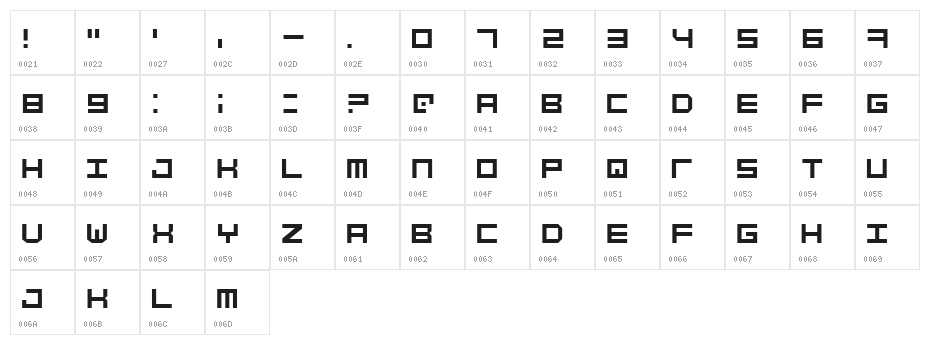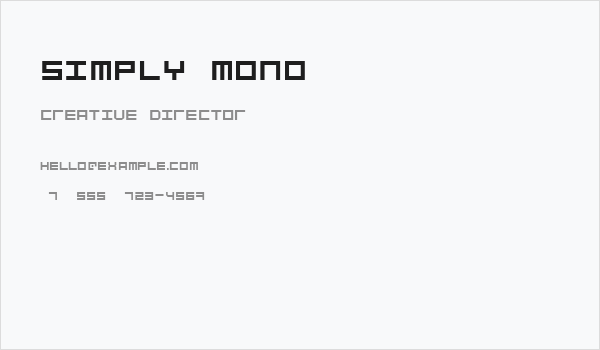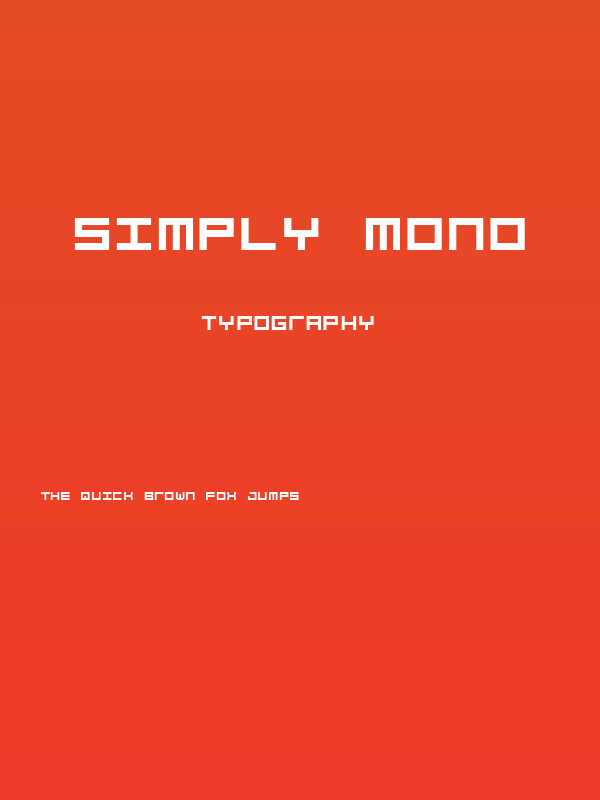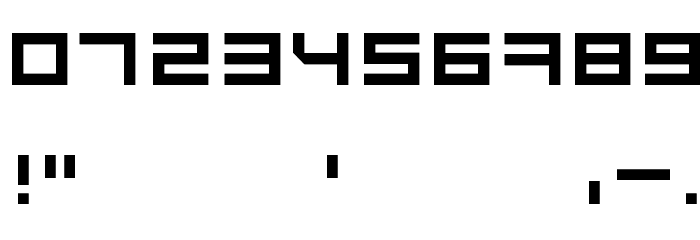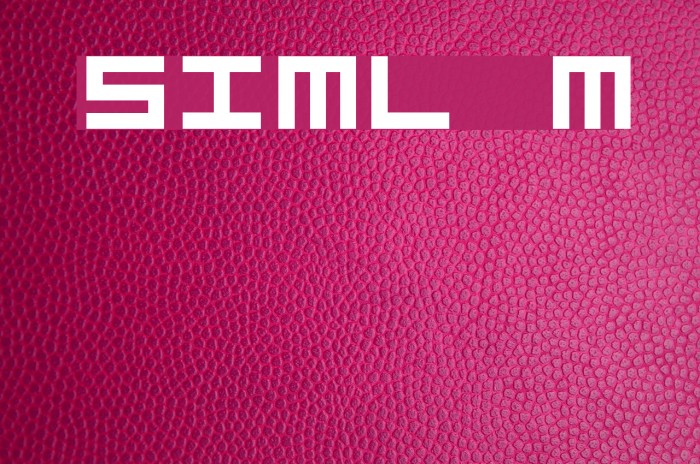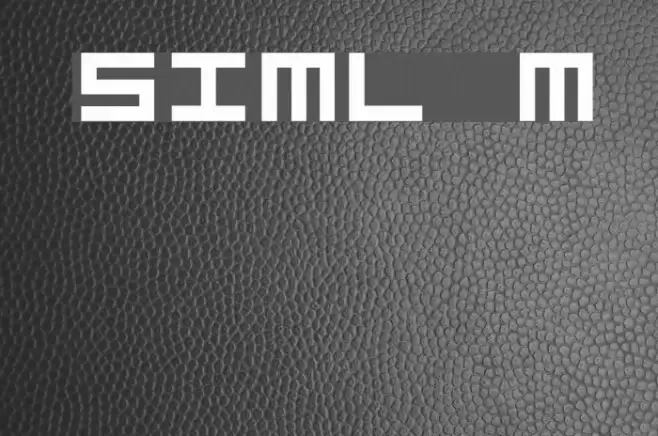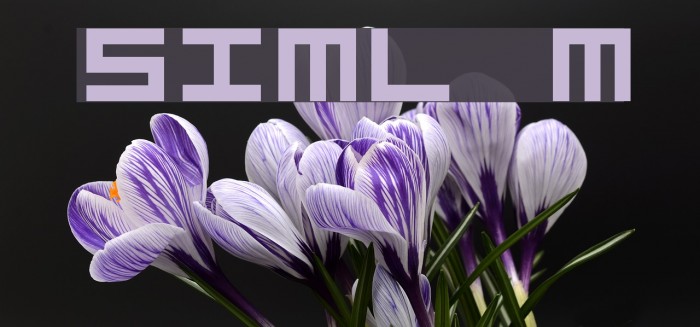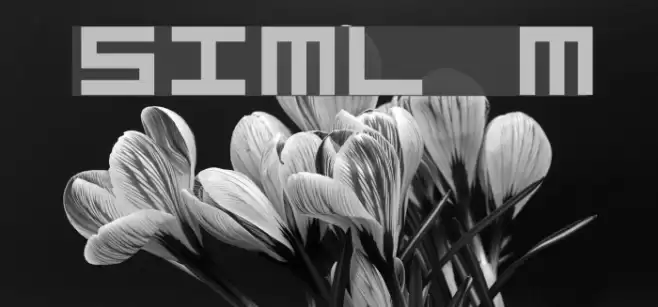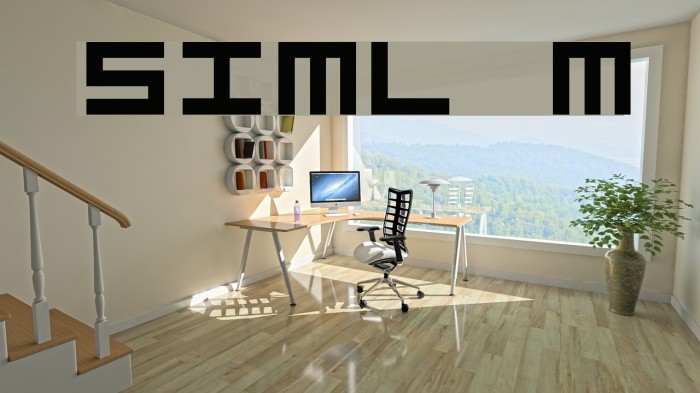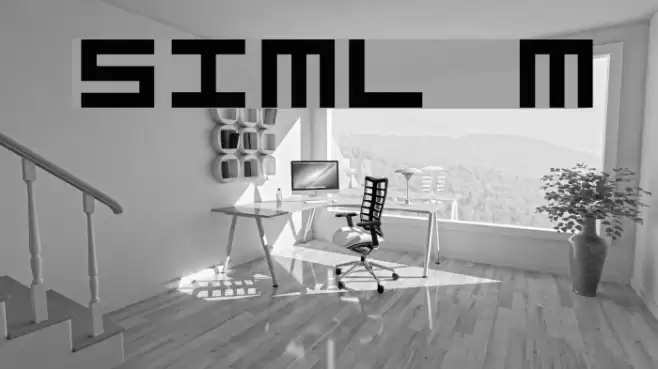
Simply Mono Font
| Категория | Typewriter |
| Область применения | Headlines, Digital displays, Coding environments |
| Рекомендуемые проекты | Ideal for coding environments, tech branding, digital interfaces, and futuristic design projects. |